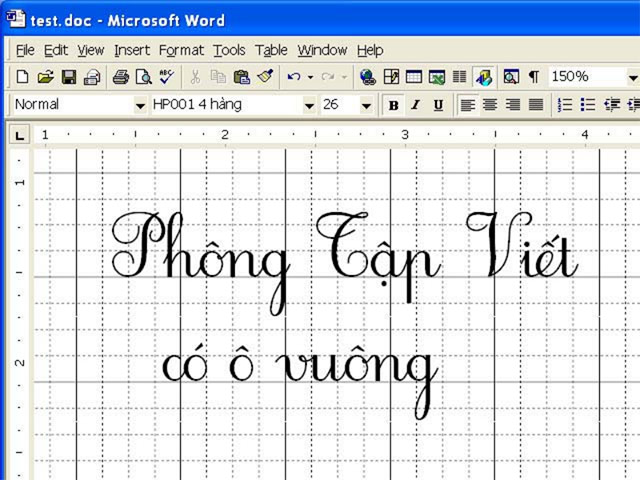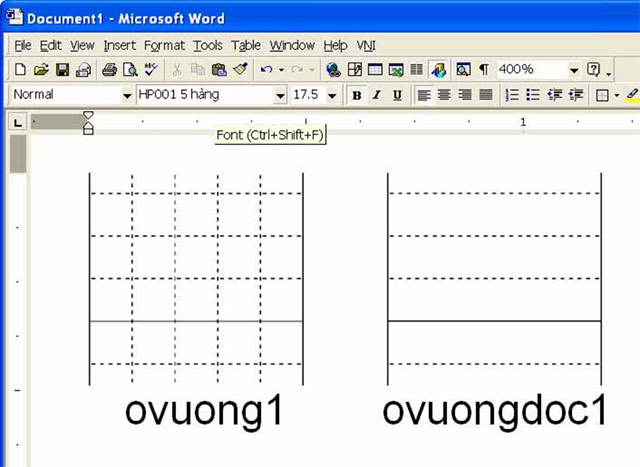
Font được thiết kế rõ nét, dễ sử dụng, hỗ trợ đầy đủ chữ cái tiếng Việt có dấu, chữ thường, chữ hoa và các ký tự cần thiết. Chỉ với vài thao tác đơn giản, bạn có thể tạo nên những trang luyện viết đẹp mắt, đồng bộ và chuyên nghiệp trên Word, PowerPoint cùng nhiều phần mềm soạn thảo khác. Ngoài ra, có thể tham khảo thêm bộ font Unicode, Font VnTime.
Bộ Font chữ tập viết có 2 loại: 4 hàng và 5 hàng. Loại 4 hàng giống vở tập viết học sinh 4 ô ly, nhưng không thể hiện được các ký tự Ô Ắ... Tất cả có 4 file font bao gồm:
Còn nếu muốn hiển thị ô vuông giống như vở học sinh thì làm như sau:
Lưu ý: Phải chọn kiểu font cho ovuong1 và textbox giống nhau. Size trong textbox gấp đôi size ovuong1 sẽ cho chữ 2 ô ly, còn bằng nhau là 1 ô ly. Nếu không cần những ô vuông có đường kẻ dọc thì dùng những font có sẵn ô ly.